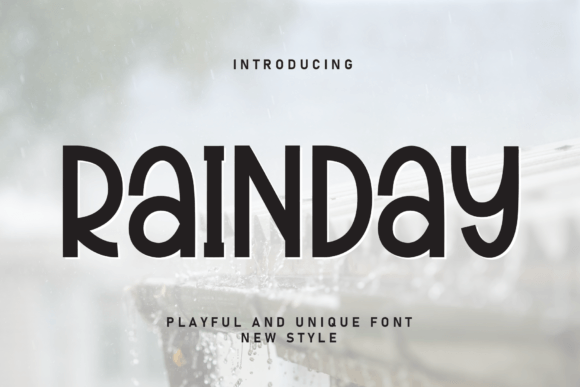
Rainday
Descubra o Encanto da Rainday
Se você está procurando por uma fonte que seja ao mesmo tempo aconchegante e clara, a Rainday é a escolha certa para você. Essa fonte sans-serif é uma combinação perfeita de acessibilidade e clareza, tornando-a ideal para projetos que precisam de um toque acolhedor e moderno.
O que a torna tão especial?
- **Formas de letras equilibradas**: A Rainday tem um equilíbrio perfeito entre os elementos de sua forma de letra, criando uma sensação de serenidade visual.
- **Curvas sutis**: As curvas da fonte são tão sutis que elas não distraem, mas sim adicionam profundidade visual ao conteúdo.
- **Versátil**: A Rainday pode ser usada em projetos de diversas áreas, desde publicidade até design gráfico.
- **Warm e aconchegante**: A fonte adiciona um toque de acolhimento e conforto ao seu design, tornando-o mais atraente para os usuários.
Por que você precisa adicionar a Rainday ao seu projeto?
É simples: a Rainday é uma fonte que realmente entende as necessidades do usuário moderno. Com sua combinação perfeita de clareza e acessibilidade, ela é capaz de transmitir seus mensagens de forma clara e eficaz. Além disso, sua estética aconchegante e moderna a torna uma escolha popular entre designers e criadores.
Então, não perca mais tempo: adicione a Rainday ao seu projeto hoje mesmo e descubra o encanto que ela pode trazer ao seu design!